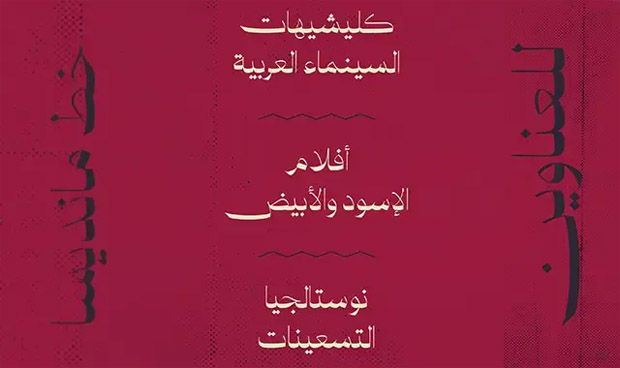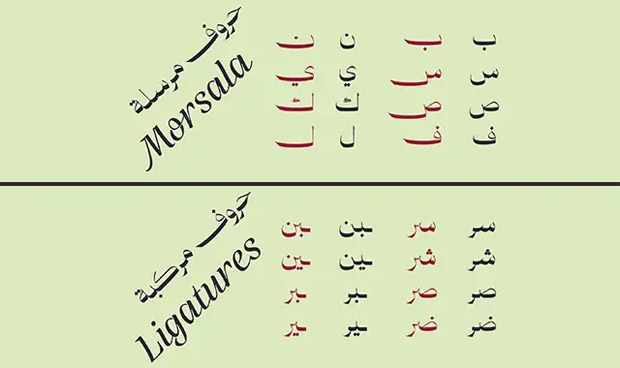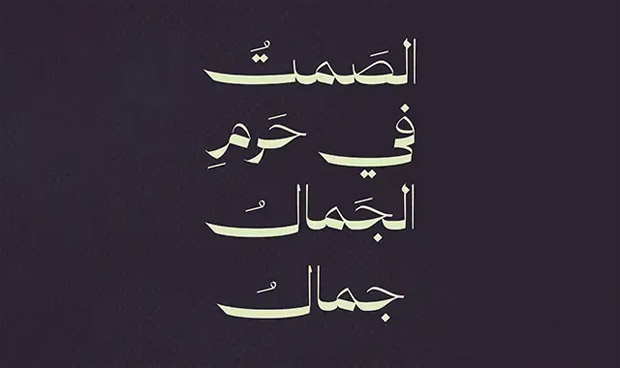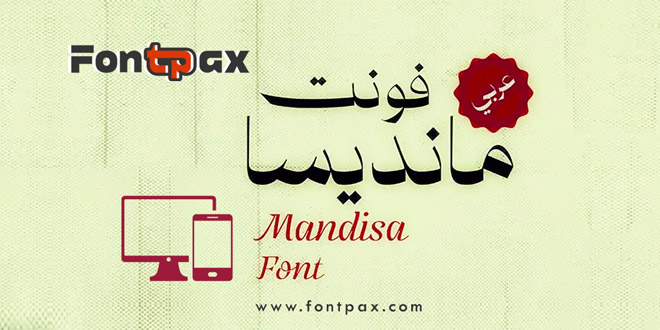
خط مانديسا العربي للحاسب والموبايل .. خط مانديسا هو خط عربي مميز شديد الوضوح وبسيط، يمكن استخدامه في العناوين الرئيسية والنصوص الفنية والشعارات، الخط متوفر بوزن واحد فقط، ويمكن استخدامه في الحاسب الآلي والموبايل، وهو متاح للتحميل المجاني الآن.